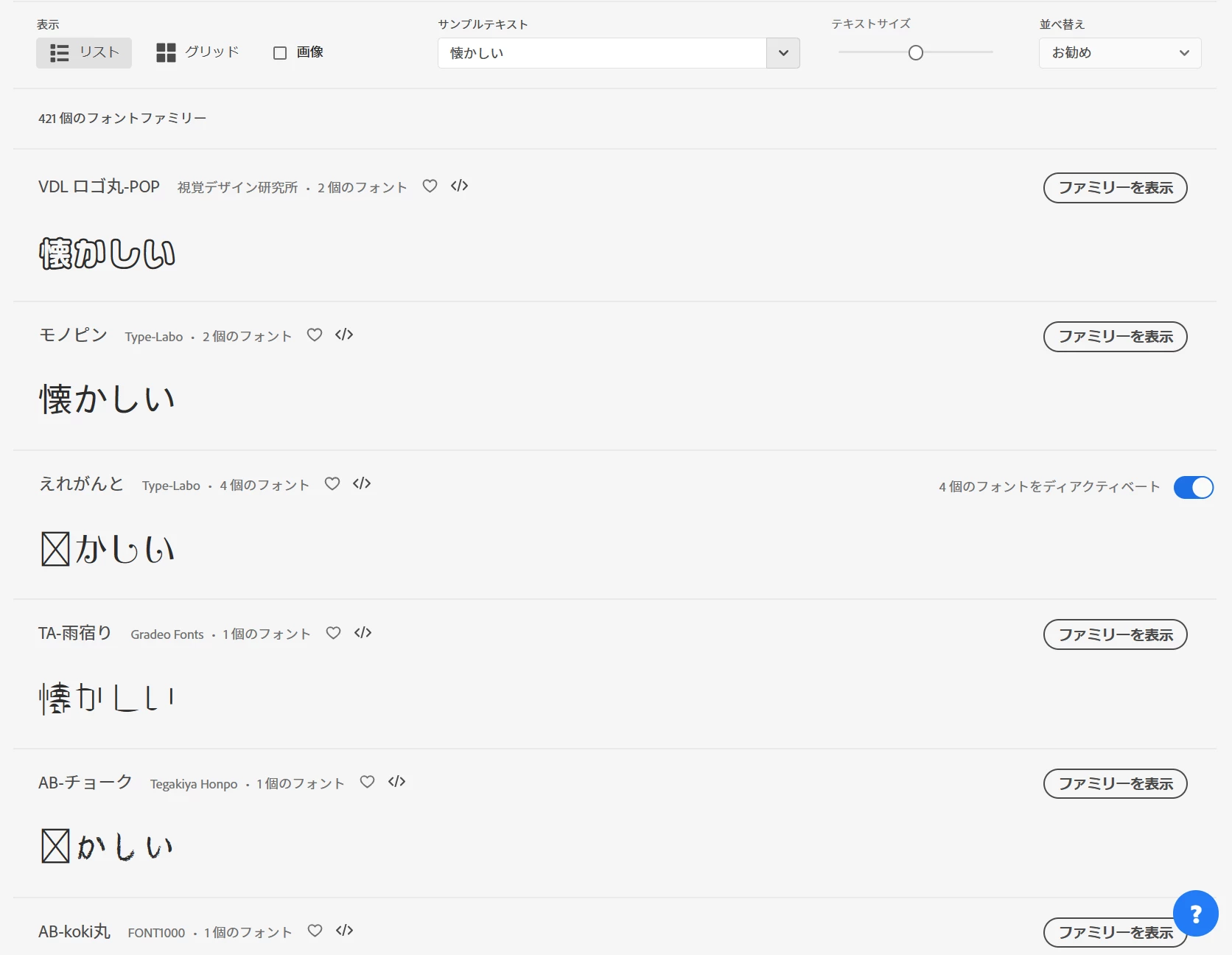
筆書体の一文字目が Photoshop で表示されない
どちらのフォーラムに投稿しようか迷ったのですが、フォントによって動きが異なるようなので、こちらにしました。同じような症状の方はいらっしゃいますでしょうか?
Photoshopの「横書き文字ツール」でテキストを書こうとしています。
楷書体の毛筆にしたかったので、Adobe Fontsから「AB-堂々楷書」をインストールしました。しかしながら、1文字目だけ表示されません。(選択すると反転するので、文字がないわけではなく、表示されないようです)
小塚明朝や心龍爽等のフォントは正常に表示され、以下のようなフォントはうまく表示されません。
• AB-堂々楷書
• AB-奈良
• OT-白舟行書教漢
同じような症状の方、いらっしゃいますでしょうか?
にアクセスして以下のように「懐かしい」とサンプルテキスト欄に入力してください。
AB~と頭に付くFont1000シリーズは「懐」が含まれていない書体です。このような書体は実用性が低く実務では使いどころが限られるものです。
例にあげられたフォントは、すべての文字が揃っているフルセット版ではなく、限られた文字のみが搭載されているフォントのようです。そのため、たまたま1文字目に来た文字が、この書体には搭載されていないのではないでしょうか?推察ですが。
試しに「あいうえお」など、どのフォントにも搭載されている文字で試してみてください。
次のAdobe Fontsページの「サンプルテキスト」に文字を入力することで、このフォントに文字が入っているかどうかを確認することもできます。
※FONT1000。ベスト1,000の漢字に両仮名および約物
※1,026 の教育用漢字、英数字、全角ひらがな、カタカナ、約物
Font1000シリーズはグリフ自体が1000しかないものです。どのような文字列を入力しているのかが不明ですが、当該文字が含まれていない可能性が高いです。また、「白舟行書教漢」も1026しかグリフが含まれないものです
常用漢字の範囲においても相当数のグリフが欠落しますので実用に耐えないフォントではありますので、利用には注意が必要です。
懐かしい という時の最初の文字が出ません。
他のグラフ数の十分あるフォントを探してみます。
にアクセスして以下のように「懐かしい」とサンプルテキスト欄に入力してください。
AB~と頭に付くFont1000シリーズは「懐」が含まれていない書体です。このような書体は実用性が低く実務では使いどころが限られるものです。